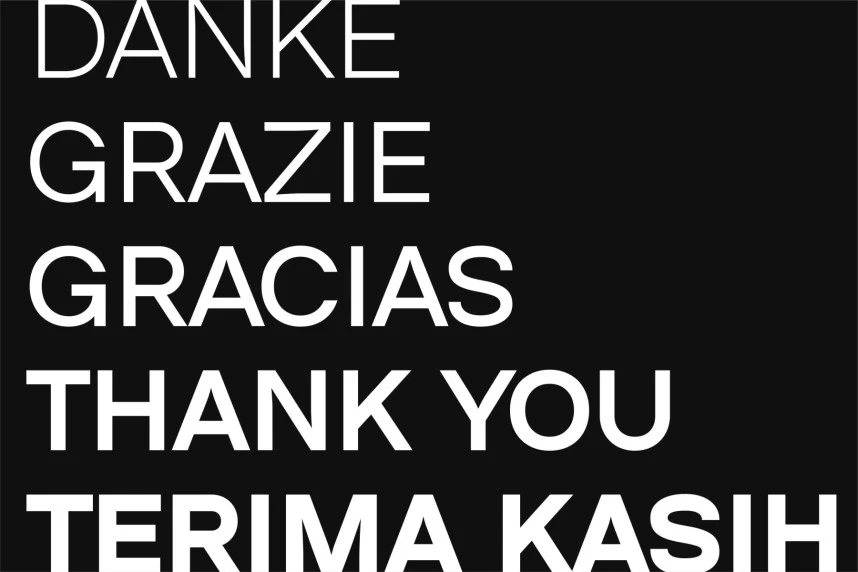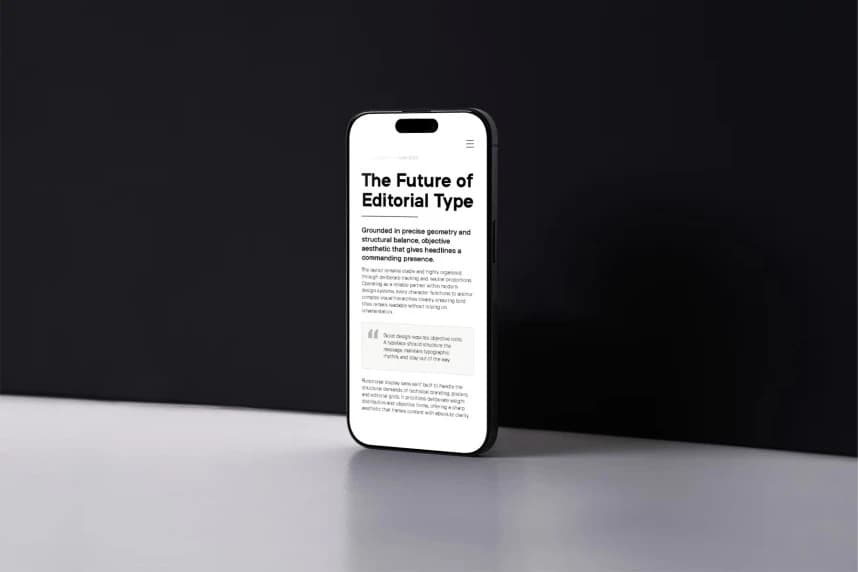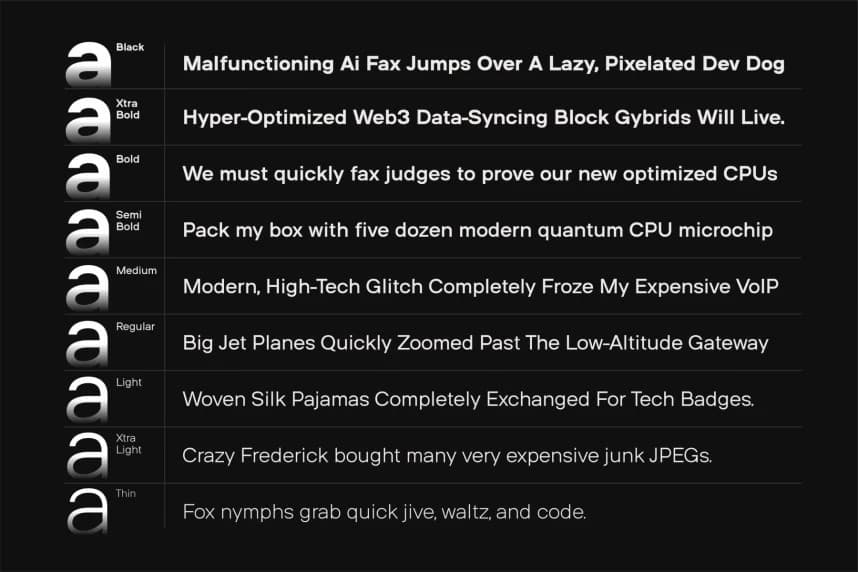
Hona Font
Hona Font Temiz, işlevsel bir gösterim sans serifidir ve özellikle teknoloji markalaşması, afişler ve editoryal düzenler için özel olarak tasarlanmıştır. Kesin geometrik yapı ve yapısal dengeye dayanan bu yazı tipi keskin, nesnel bir estetik sunar ve başlıklara baskın bir görünüm kazandırır.
Hona Font, teknoloji markalaşması, posterler ve editöryal düzenler için özel olarak tasarlanmış temiz ve işlevsel bir gösterim sans serif yazı tipidir. Kesin geometrinin ve yapısal dengenin temellerine dayanan bu yazı tipi, başlıklara baskın bir duruş kazandıran keskin, tarafsız bir estetik sunar.